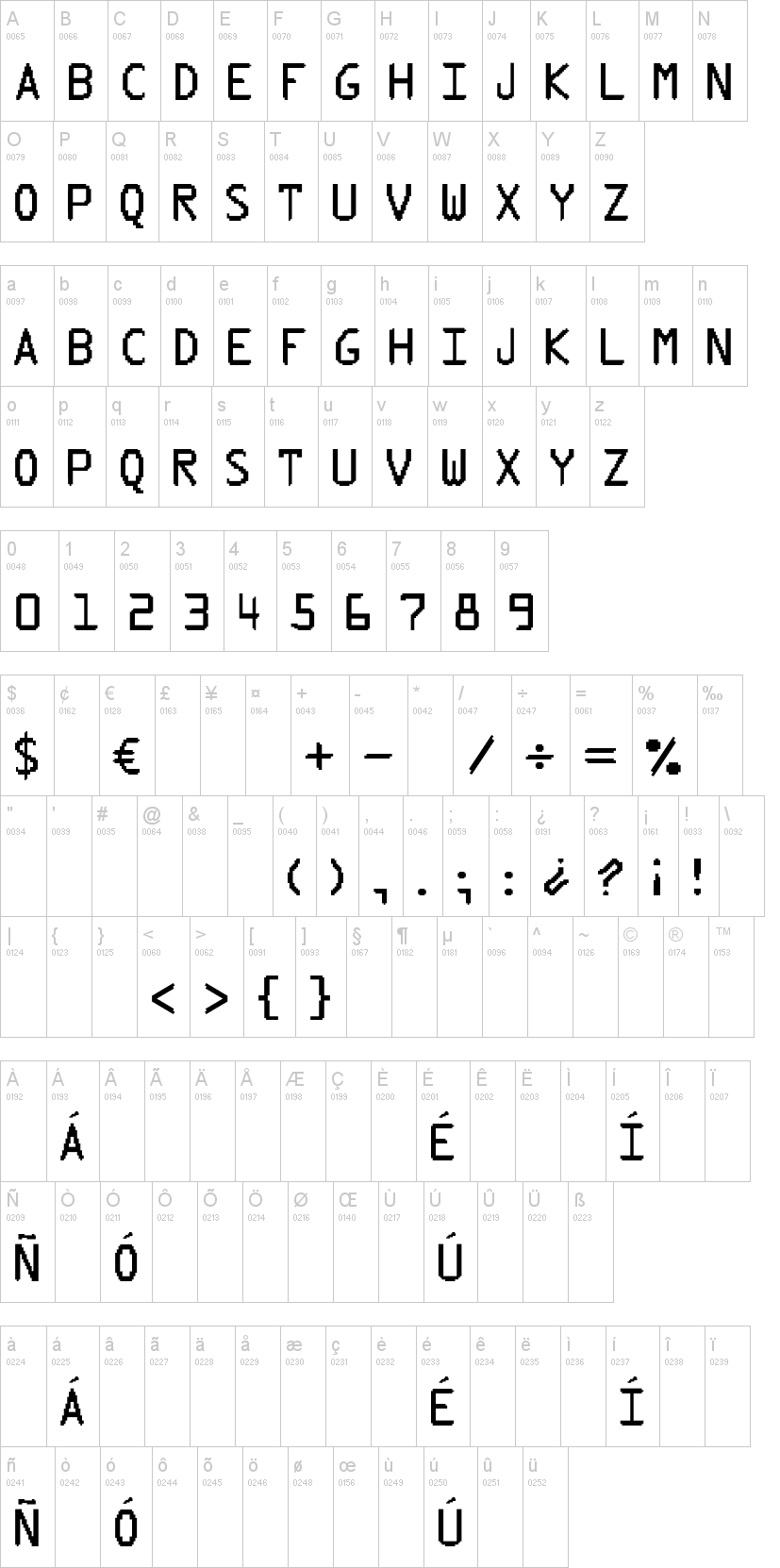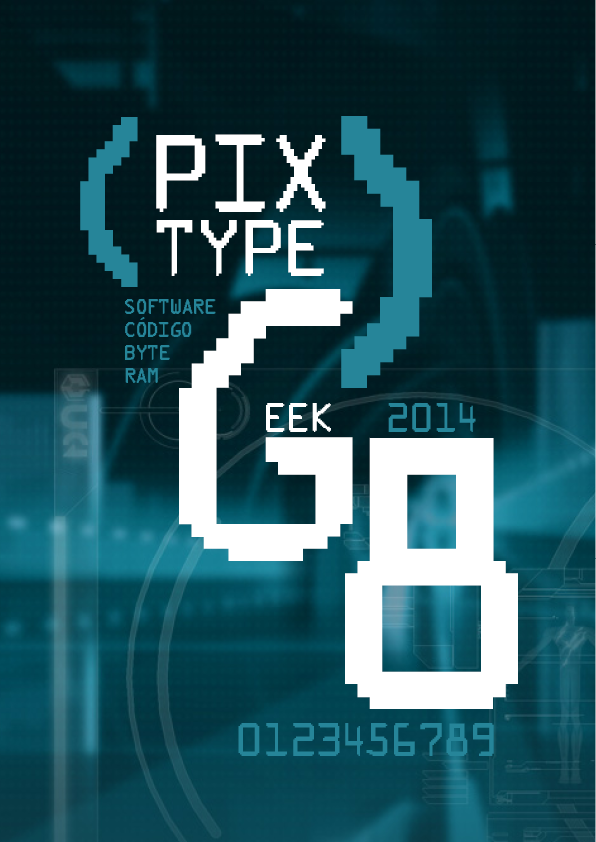
Note of the authorPix Type es una fuente display en caja alta inspirada en la cultura Geek. Ha sido construida basandose en la estructura de mapa de bits.